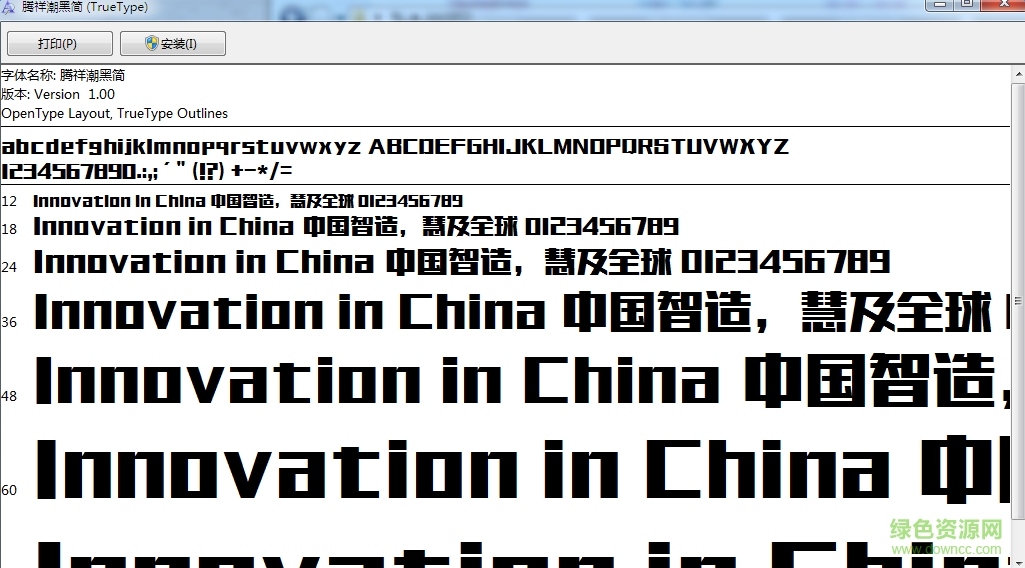
騰祥潮黑簡
騰祥潮黑字體是一款黑體粗字體,為了調(diào)整黑白空間在筆畫交叉處特別做了墨跡處理,使整體筆畫看起來既粗壯醒目又清晰易讀。適合標(biāo)題用字,可用于印刷出版、包裝設(shè)計(jì)、廣告設(shè)計(jì)、網(wǎng)頁設(shè)計(jì),有需要的朋友歡迎來綠色資源網(wǎng)下載!
字體簡介
騰祥潮黑字體字形結(jié)構(gòu)扁方、端莊,橫豎筆畫粗細(xì)比例適度、豎筆粗壯有力,布白均勻、行文貫通。字體風(fēng)格字形飽滿富于張力;筆畫硬朗簡潔表現(xiàn)清晰;為了起到裝飾效果左右結(jié)構(gòu)字形在不影響閱讀的前提下,部分點(diǎn)和提、撇和點(diǎn)做連筆畫處理,更好的展現(xiàn)出字形的連貫性和整體感!
騰祥潮黑字體